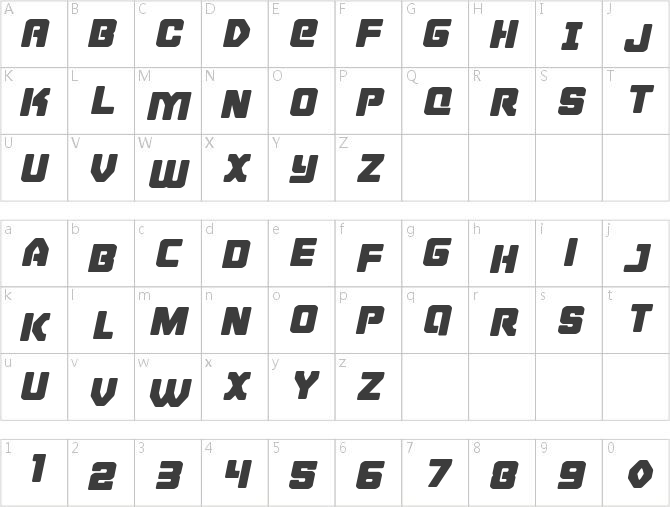
Cyborg Rooster Expanded Italic 詳情頁
字體名稱: Cyborg
Cyborg Rooster Expanded Italic
Cyborg Rooster Expanded Italic字體字庫是一款讓人賞心悅目、百看不厭的英文字體,適合各類廣告和產品包裝設計應用,字體大小0.05MB,格式為ttf字體,上傳用戶是KISEKI,作者/版權方為未知